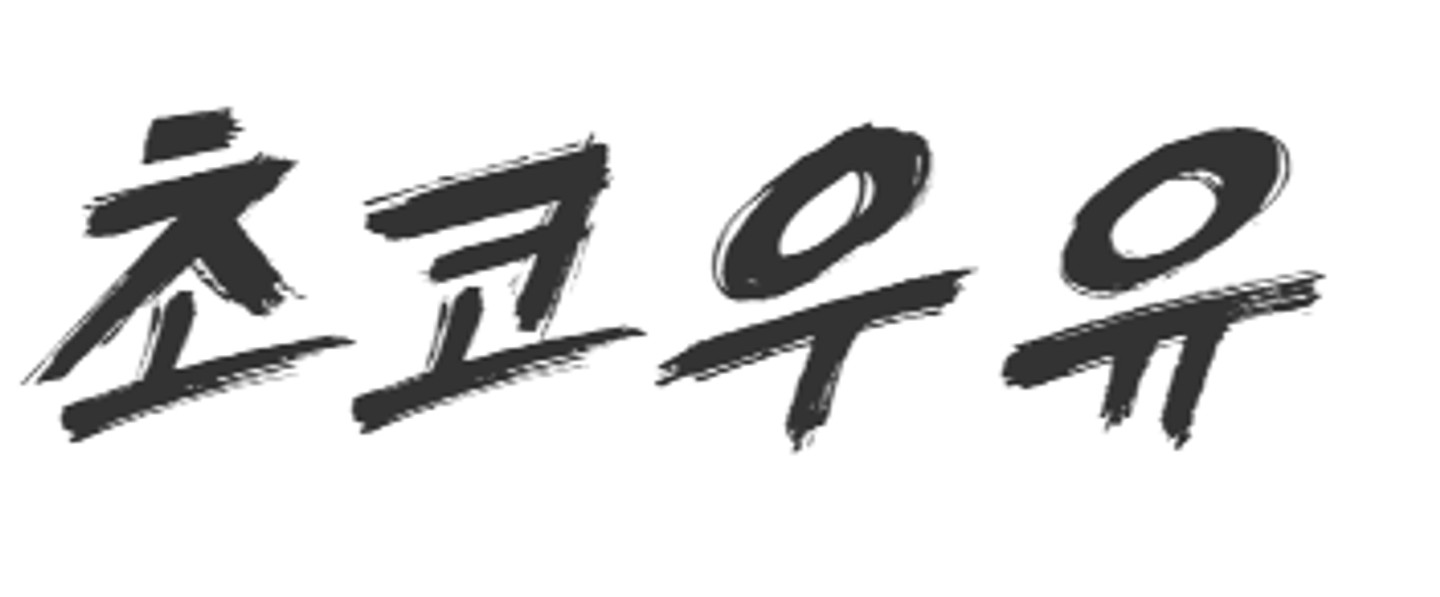
Soul 무풍지대
지피티가 만들어준 이미지의 폰트는 대부분 다른 폰트를 변형하거나 아니면 자기가 만드는 경우가 많아서 똑같은 폰트를 찾을 수가 없어요! 붓느낌 나는 폰트를 찾으신다면 Soul 무풍지대(유료)폰트 추천드립니다! https://www.sandollcloud.com/font/22096/Soul-Mupungjidae